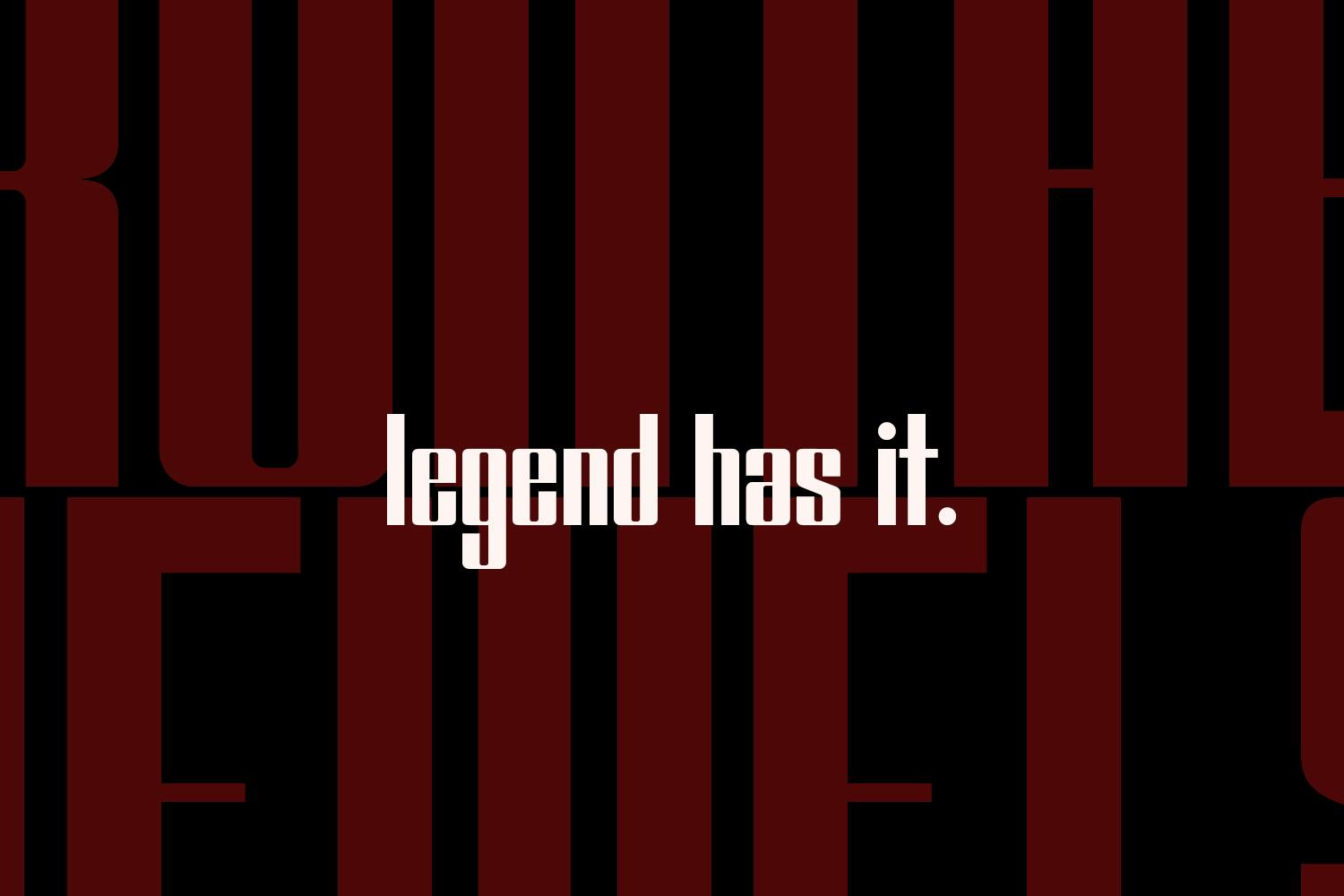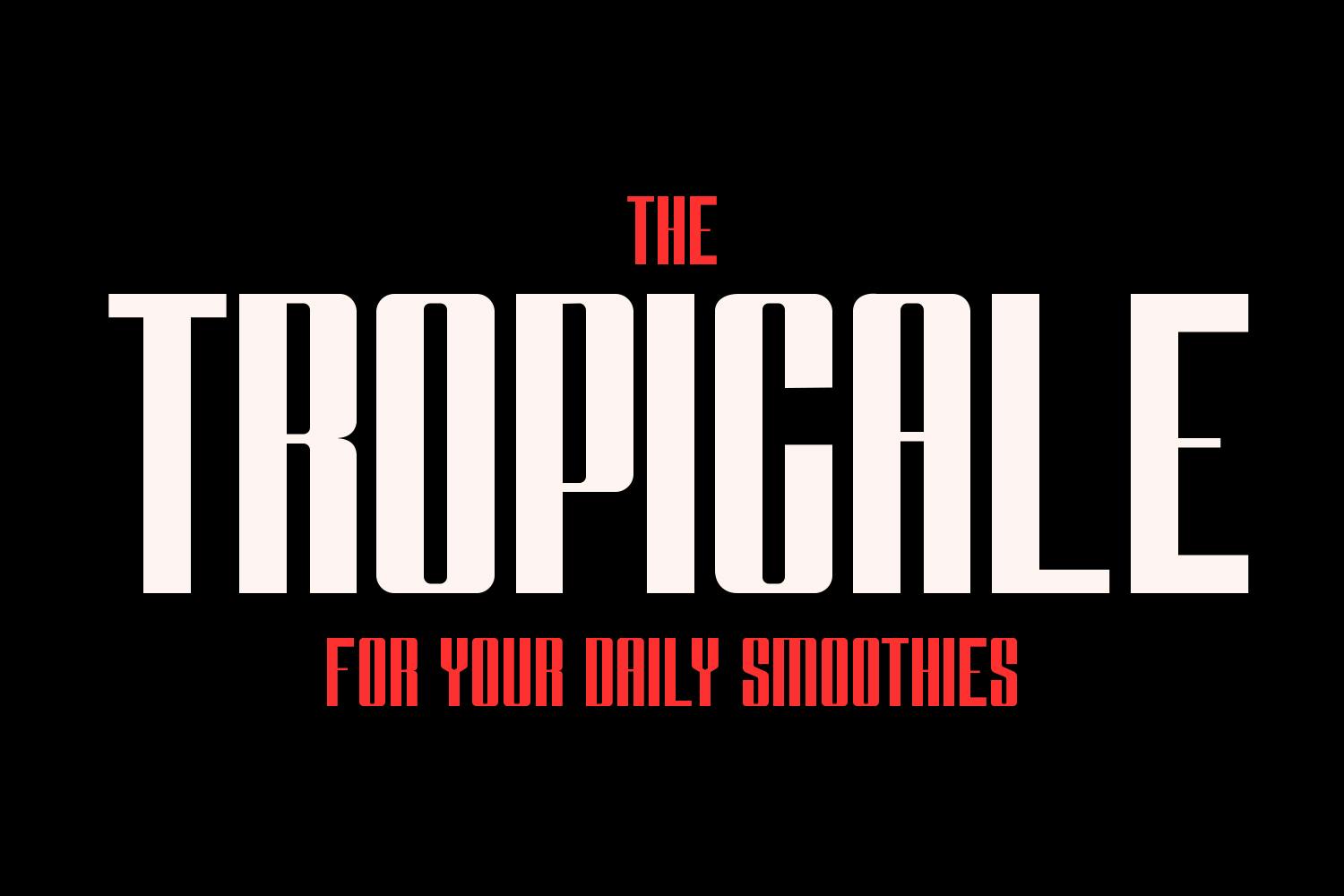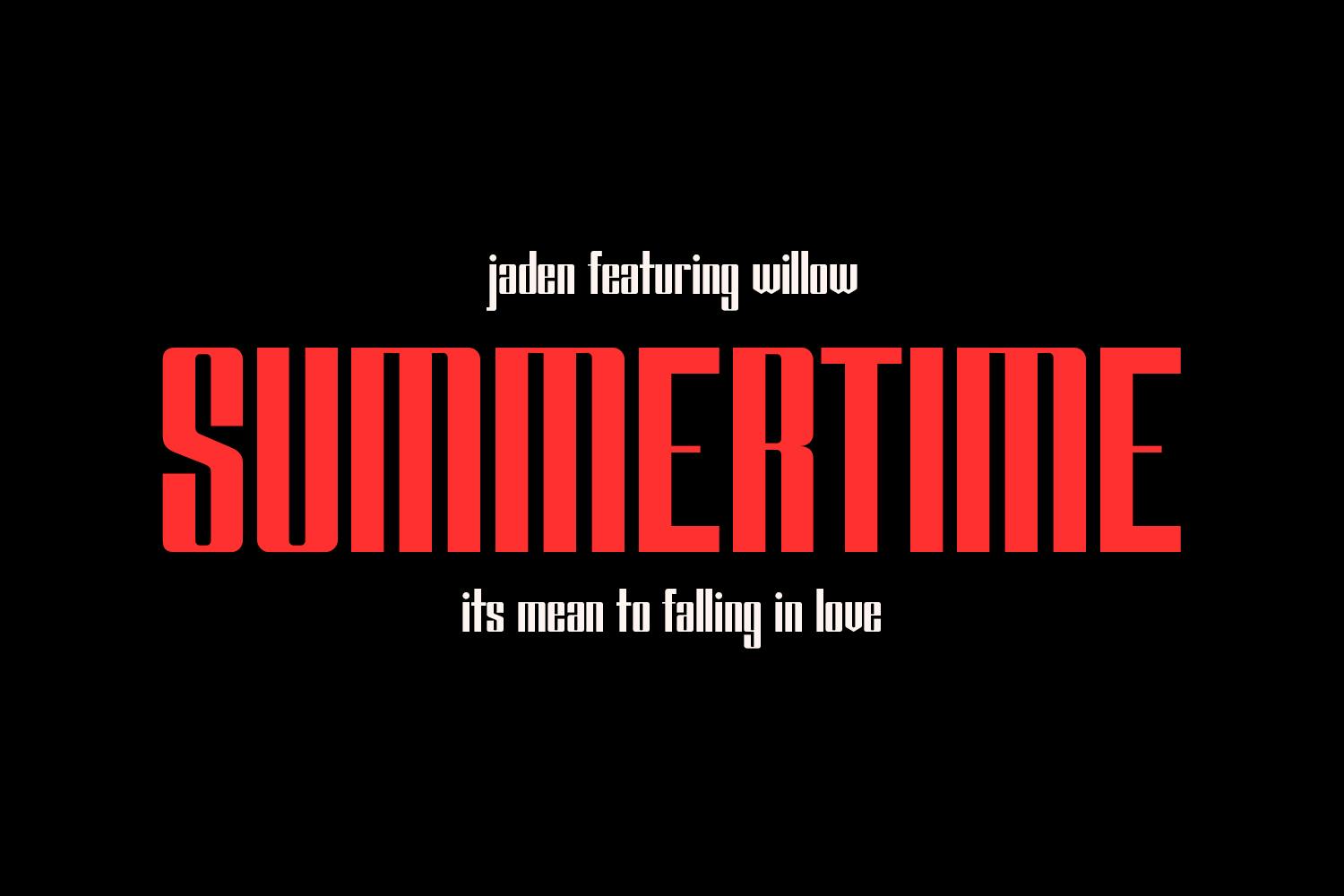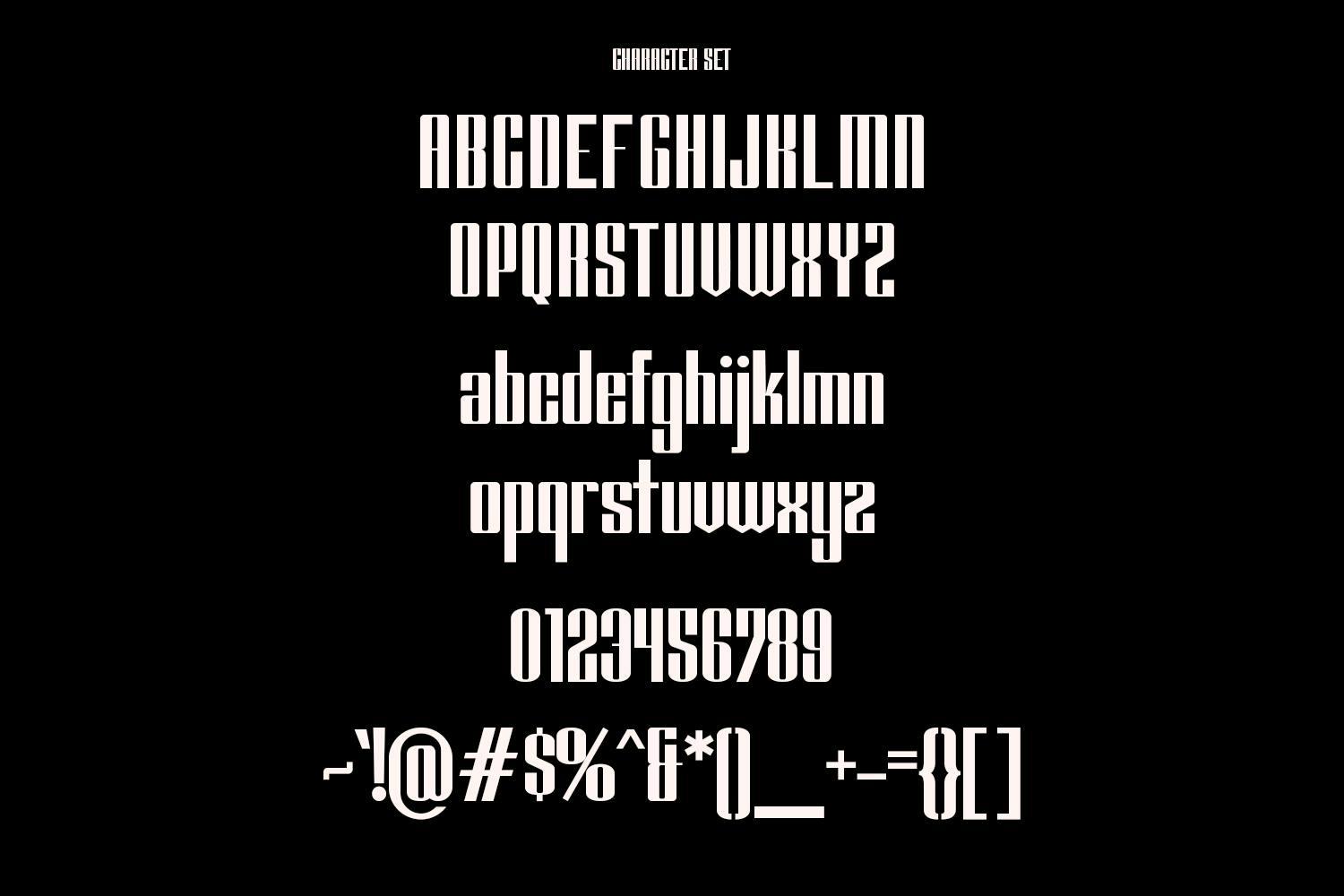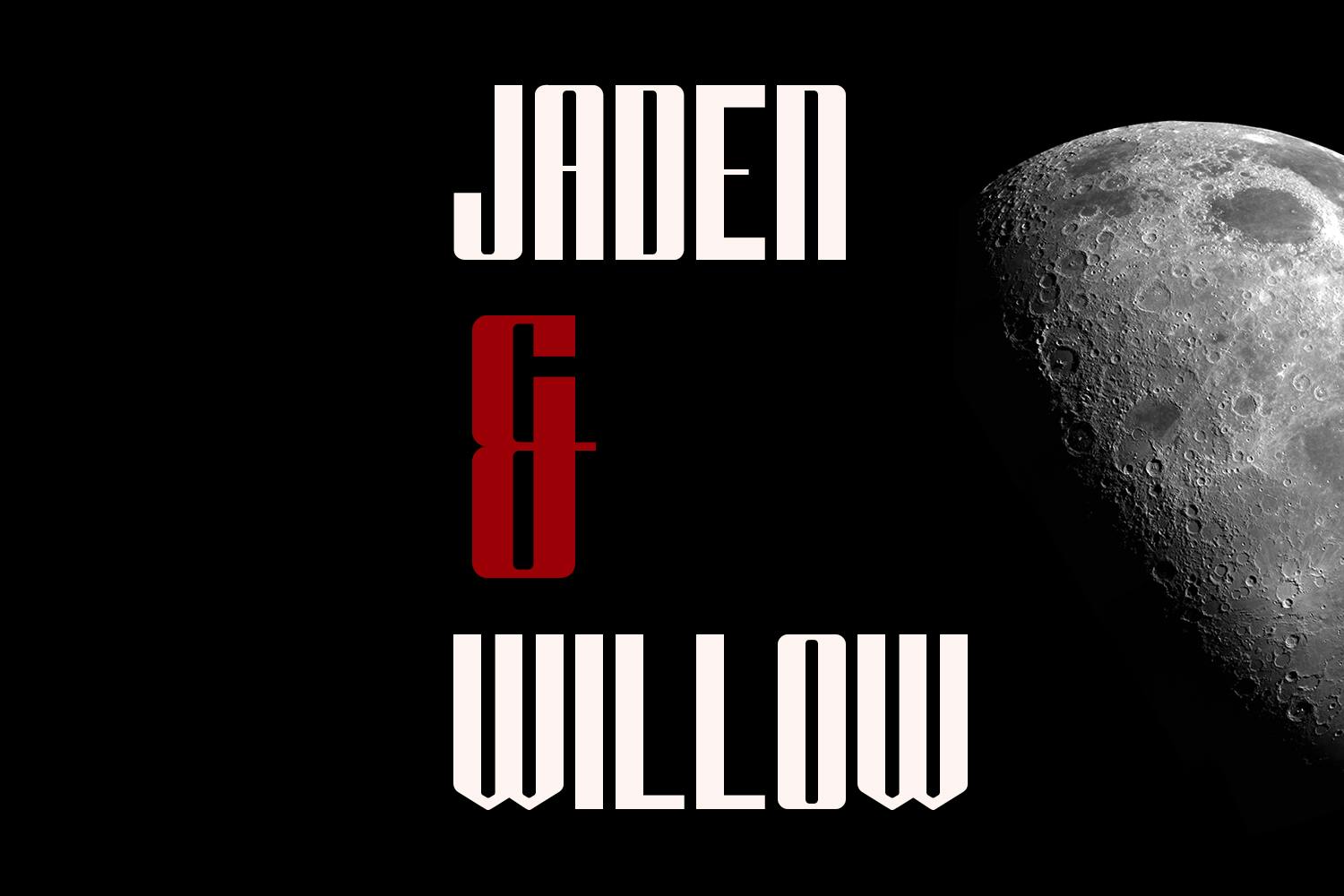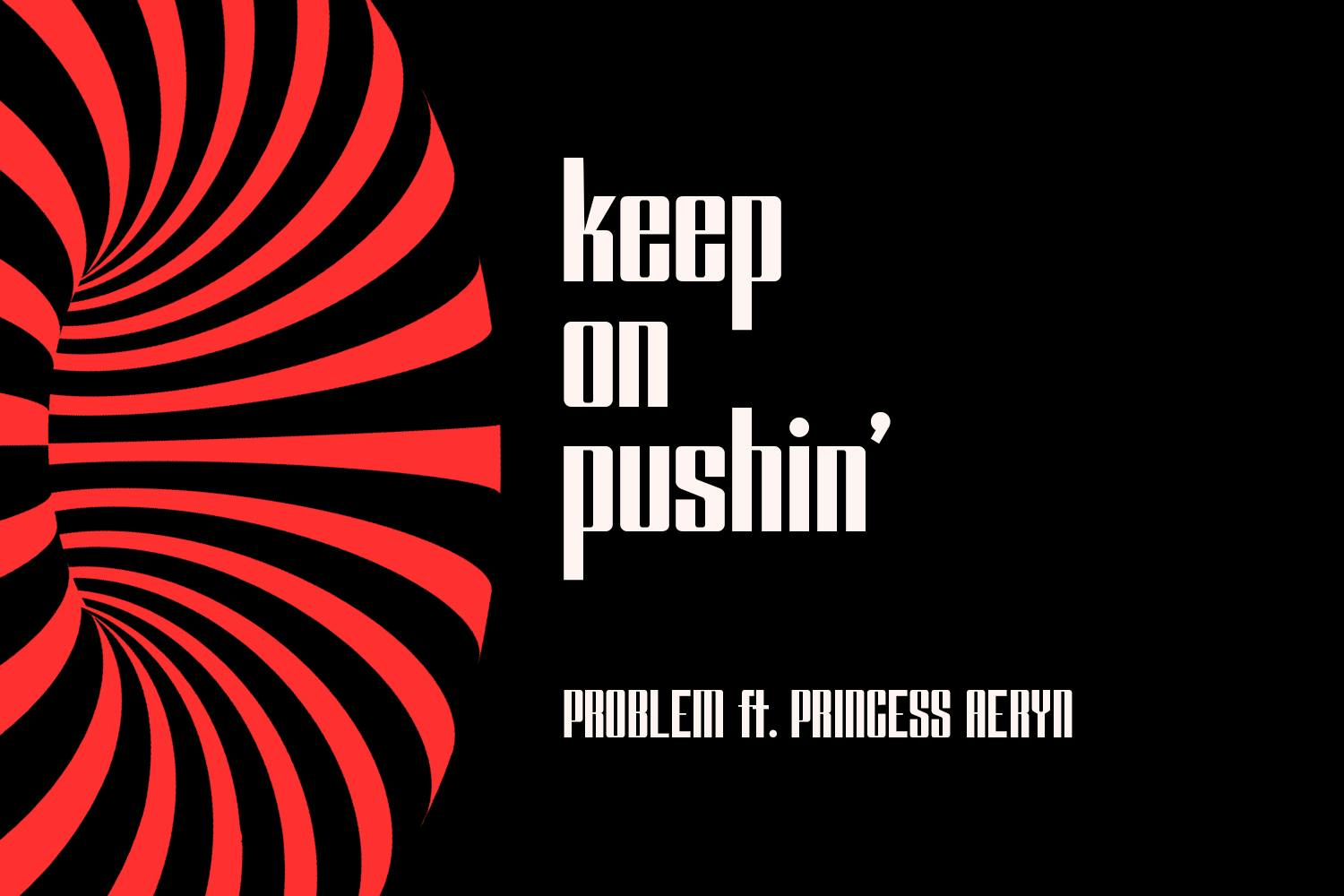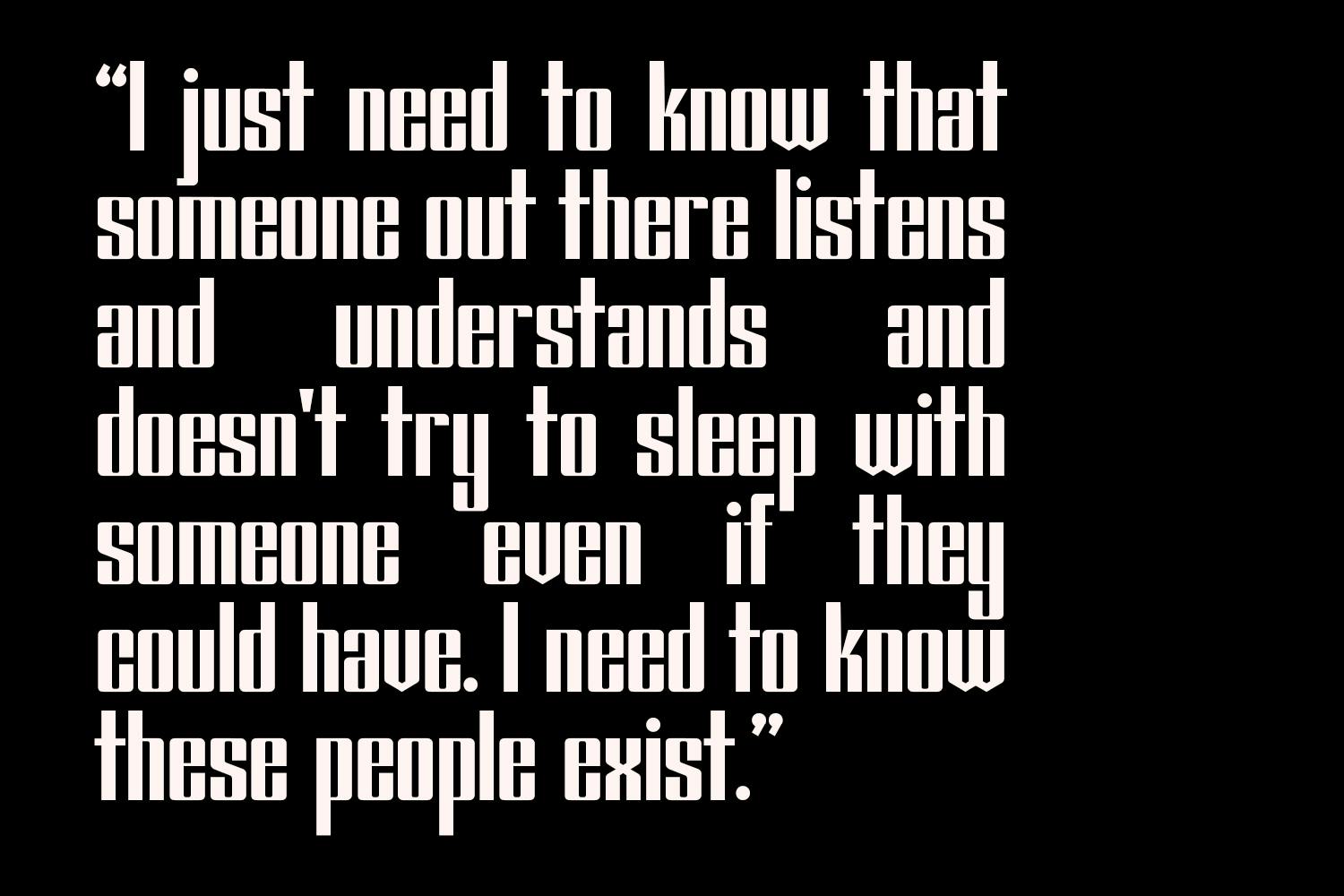
فونت اوکترز یک فونت نمایش با حس صنعتی و تکنولوژیک است. این فونت با کنتراست متوسط و ویژگیهای جذاب شامل لیگیچر و جایگزینها، به شما امکان میدهد تا آثار خلاقانهای را خلق کنید. فونت اوکترز از بیش از 100 زبان مختلف پشتیبانی میکند و برای طراحی لوگو، رسانههای اجتماعی، عناوین فیلمها، عناوین کتابها و حتی متنهای کوتاه و بلند مناسب است. این فونت همچنین به عنوان فونت ثانویه با فونتهای سانس یا سریف عالی عمل میکند. با فونت اوکترز، آثار خیرهکنندهای خلق کنید.